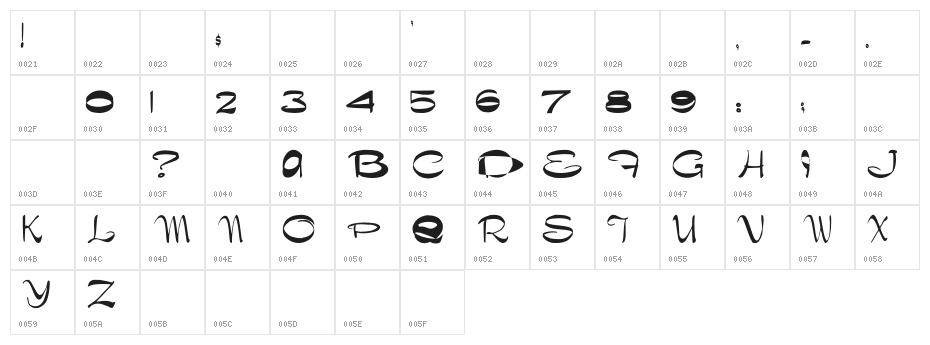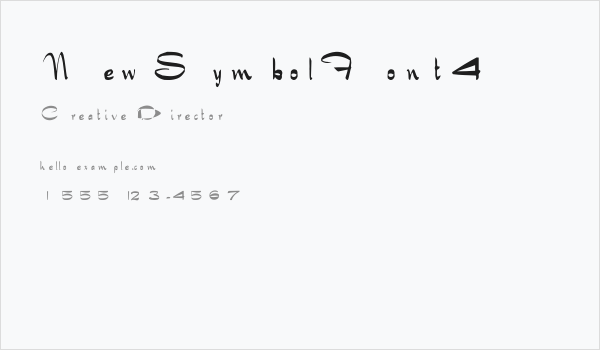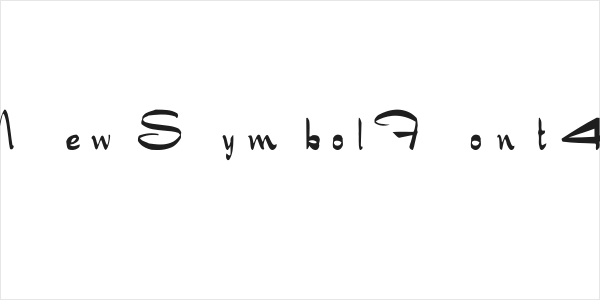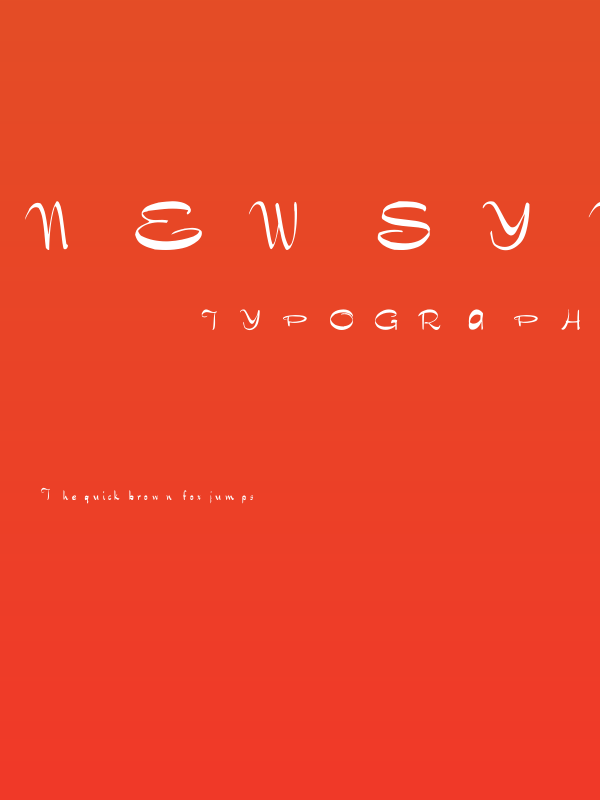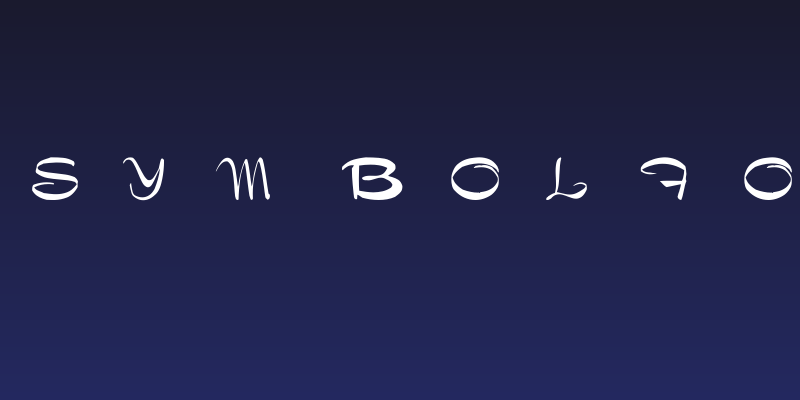
NewSymbolFont4 Font
| Stile generale | Artistic |
| Caso d'uso | Logos, Posters, Artistic Branding |
| Progetti proposti | Ideal for creative projects such as posters, album covers, and artistic branding. |